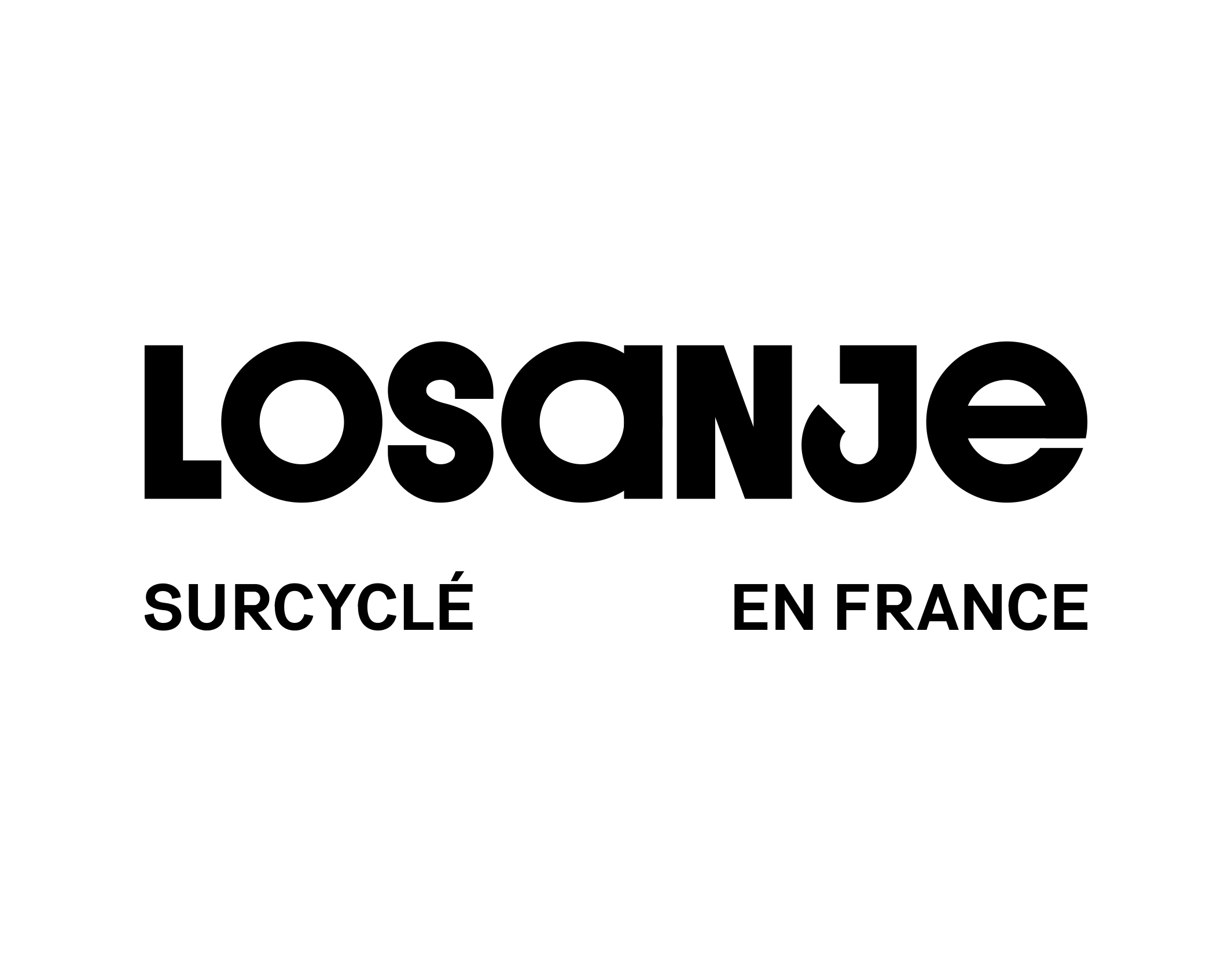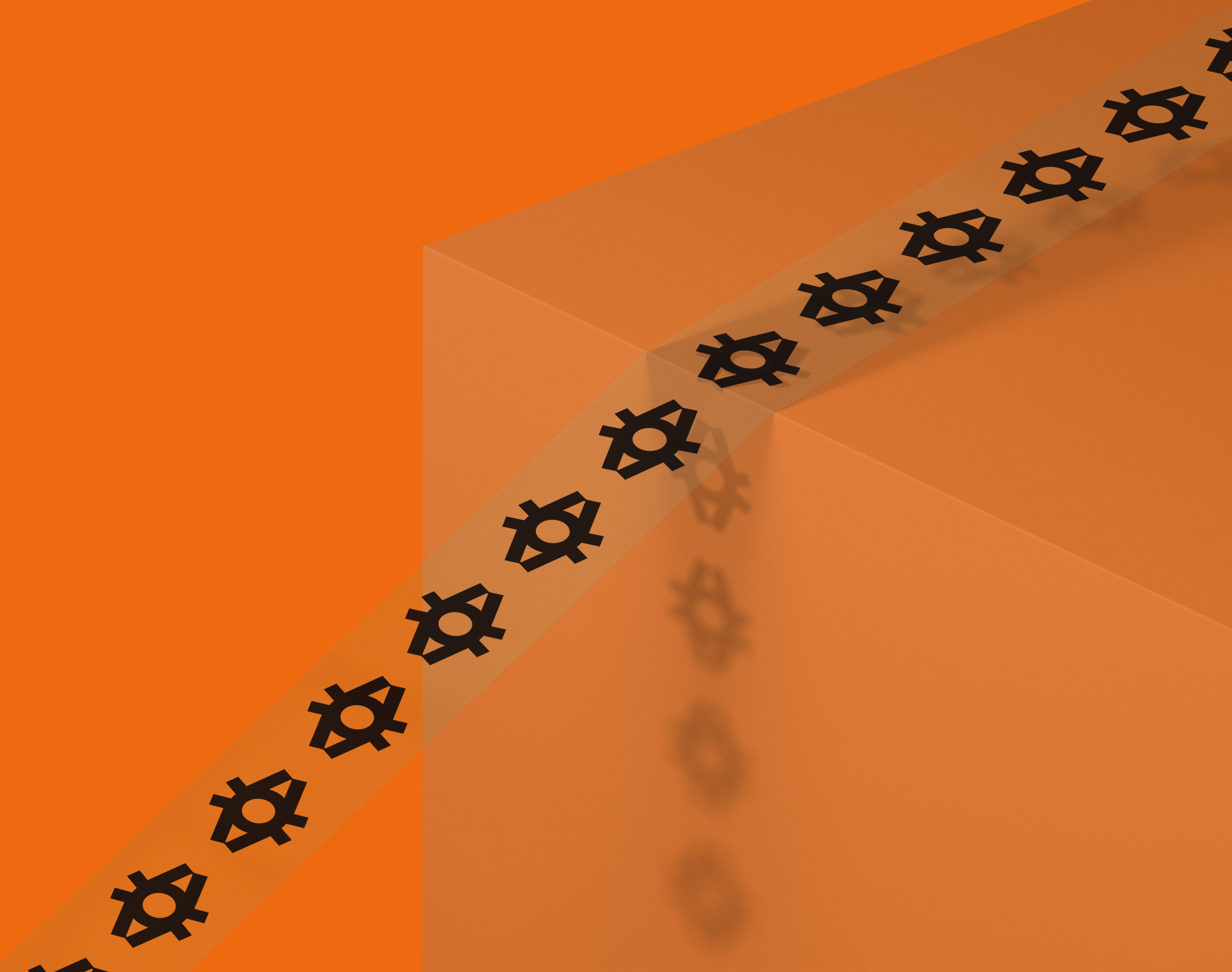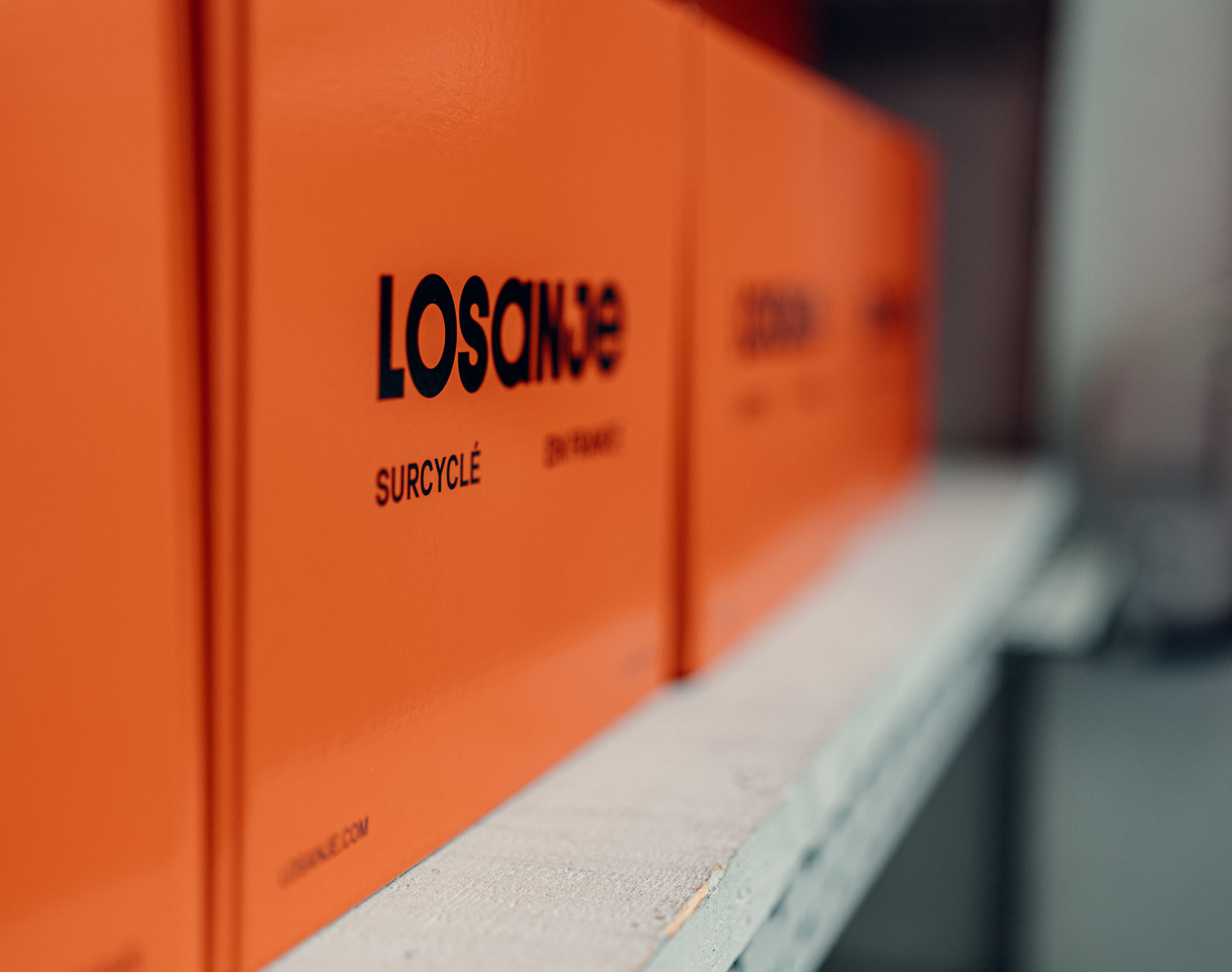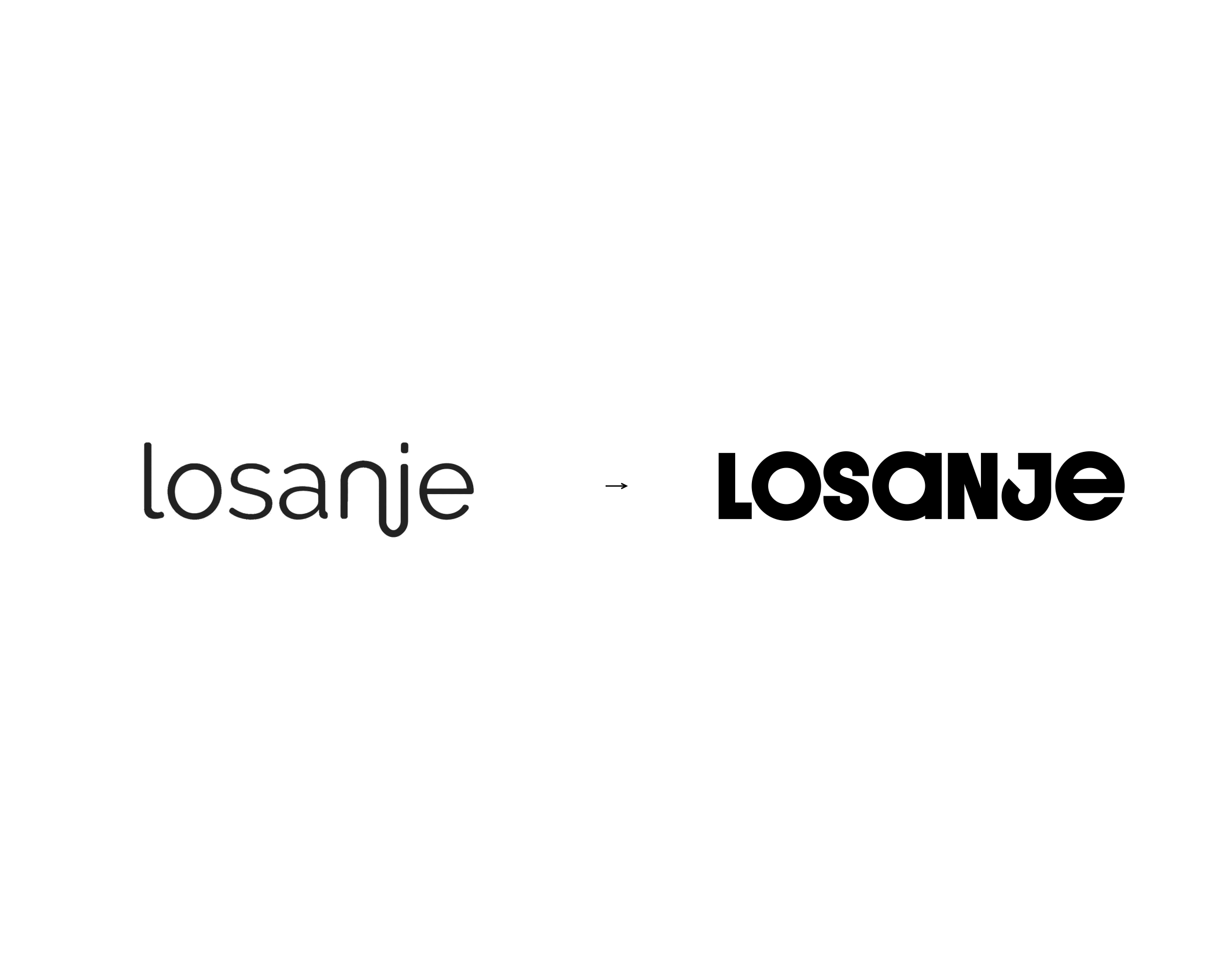
Losanje
Losanje redéfinit l'upcycling avec des vêtements responsables et une identité graphique audacieuse, alliant style intemporel et expérience client unique
Losanje est une marque créée dans l’objectif de définir le modèle de production le plus vertueux possible pour la planète, tout en dépassant les limites actuelles de la production upcyclée de vêtements. Une marque à l’image de ce que doit devenir l’upcycling : accessible en termes de style, intemporel tout en restant tendance, et qui offre la même expérience client que l’achat d’un vêtement neuf. Des vêtements responsables, utilisant pour unique matière première des vêtements et des textiles (draps, rideaux, etc) de seconde main. Créée à Nevers, l’atelier Losanje est installé dans un ancien garage de voiture, également ancien lieu d’impression de nombreuses enseignes neversoises.
Brand Brothers a été approché par le fondateur de Losanje pour offir à la marque une redéfinition complète de son identité graphique. Nous avons opté pour une approche brute mais avenante, basée sur un caractère entièrement dessiné pour l’occasion, alternant entre le haut de casse pour les consonnes et le bas de casse pour les voyelles. Le monogramme prend le contrepied des intentions classiques, en formant un oeil sur la base du typogramme. Une collection de signes sur une base similaire est ainsi appelée à naître, qui sera notamment confectionnée en broderies. La nouvelle identité a été déployée sur différents supports durant l’hiver 2022, et a été inauguré sur la collection de printemps.